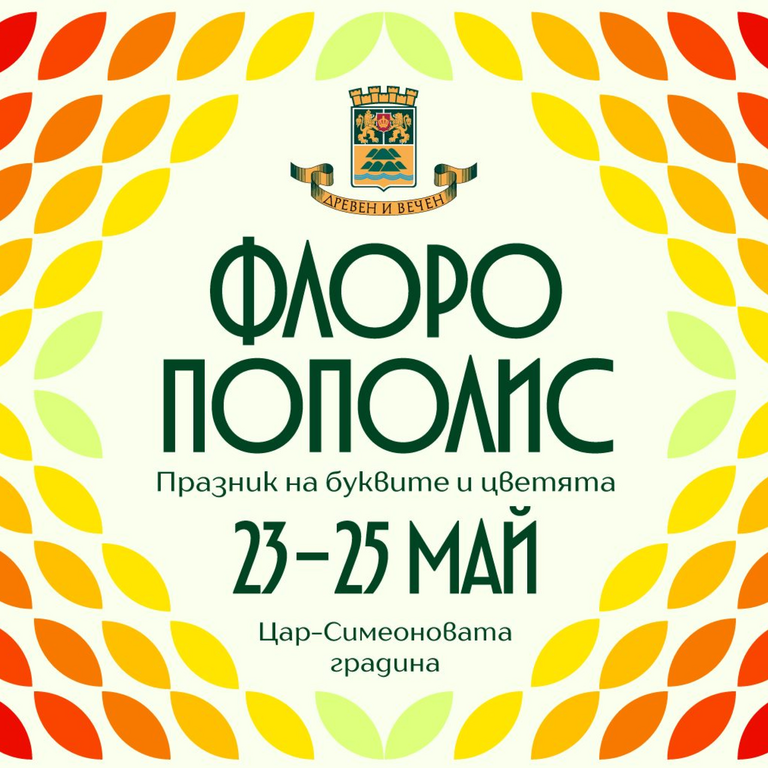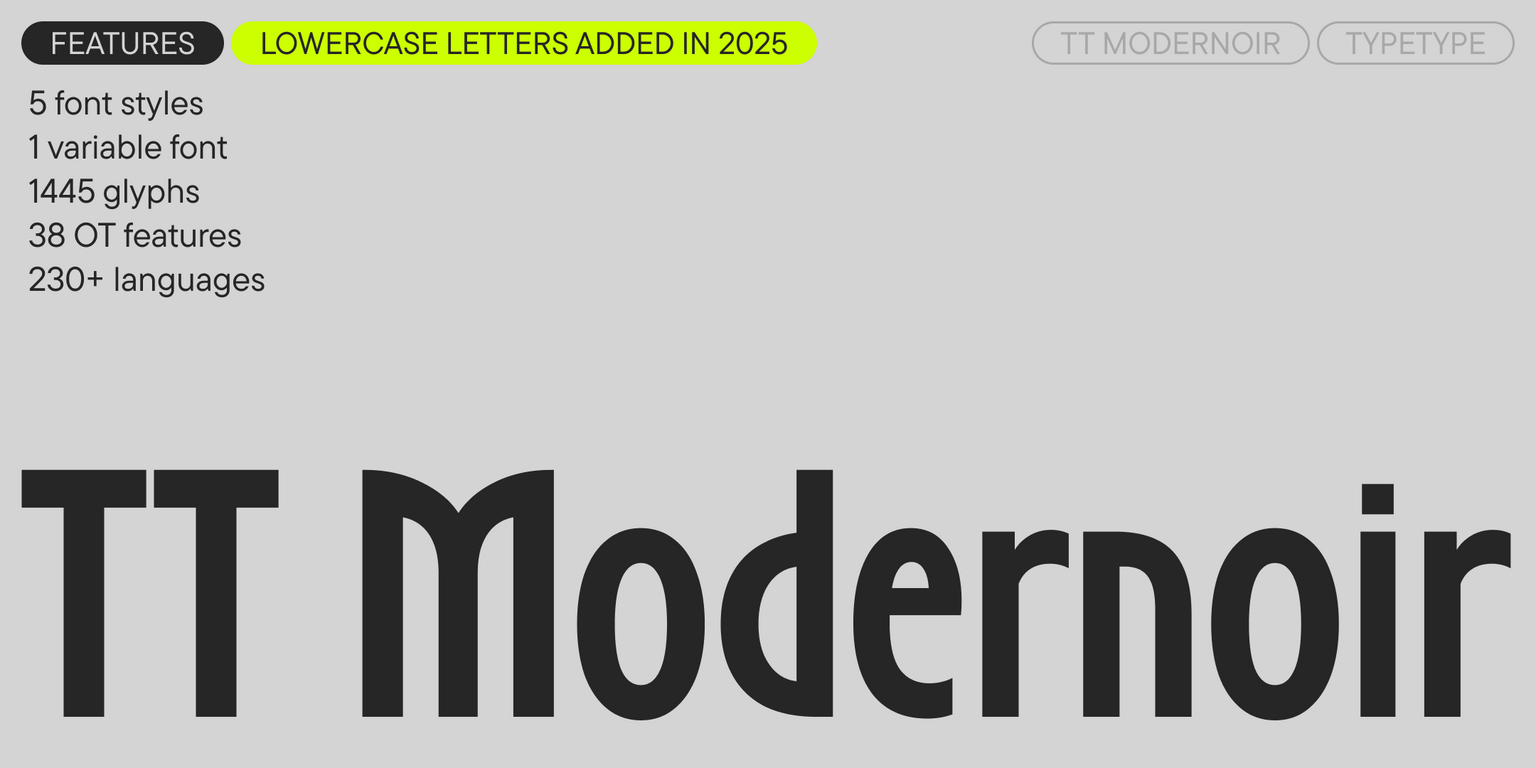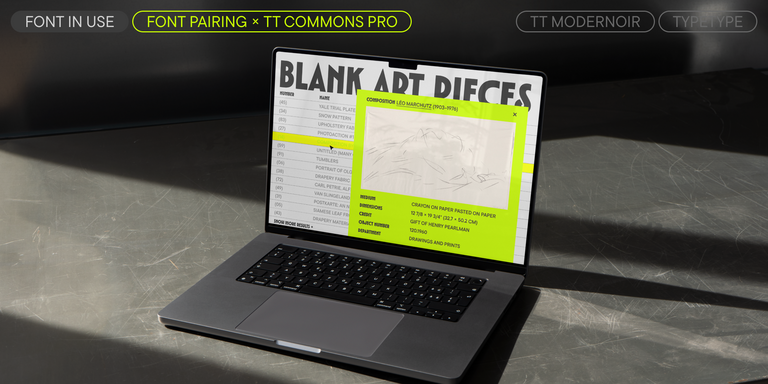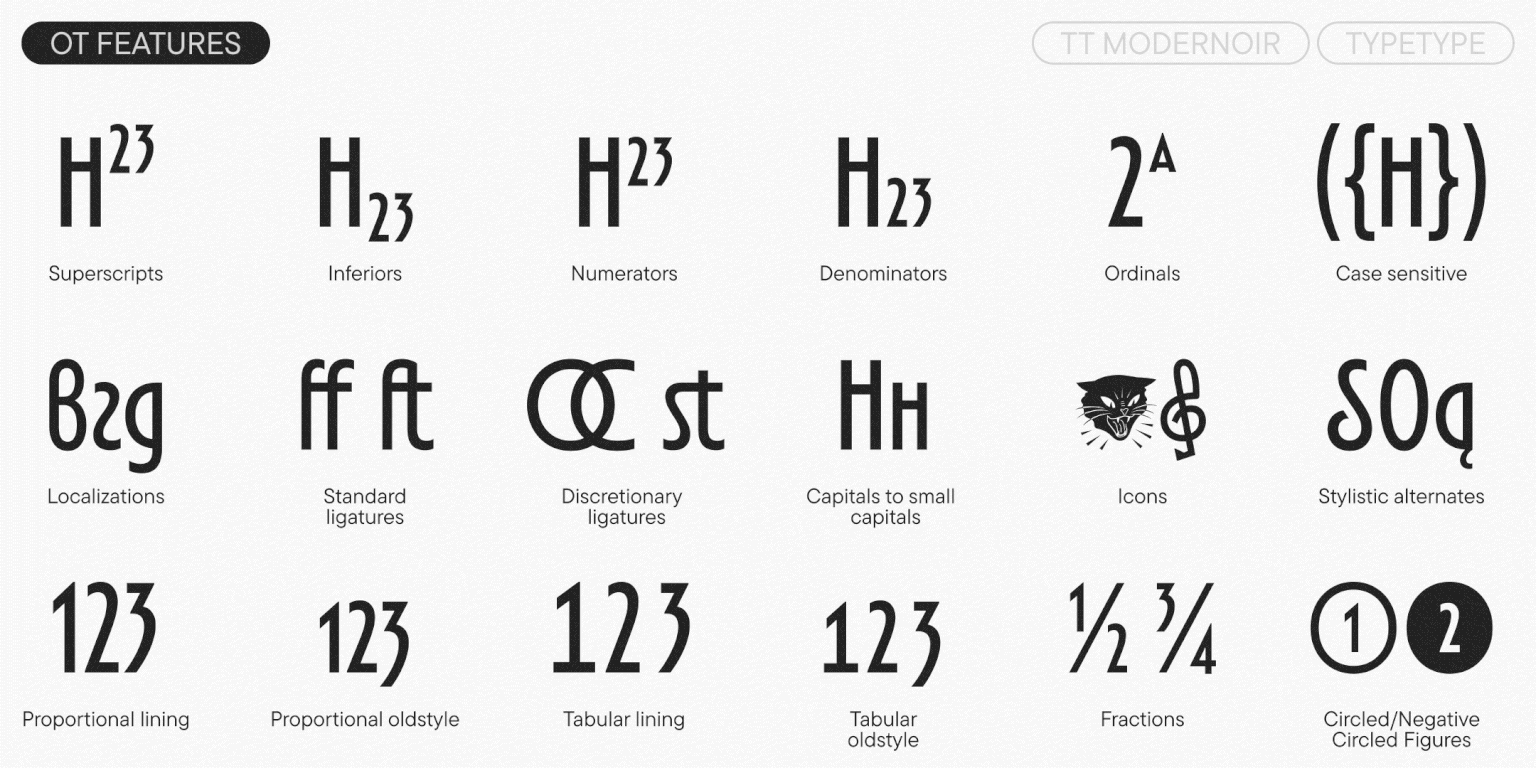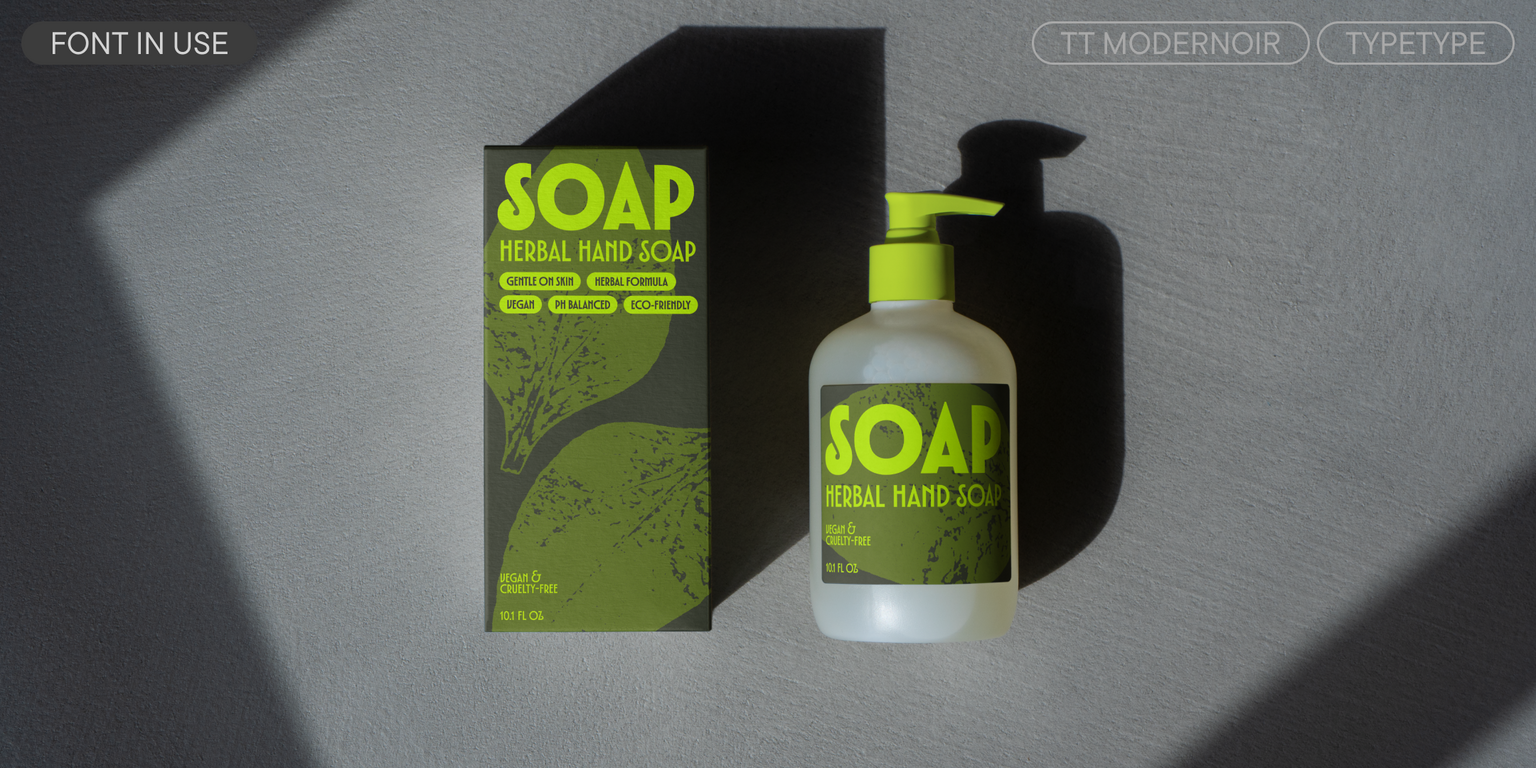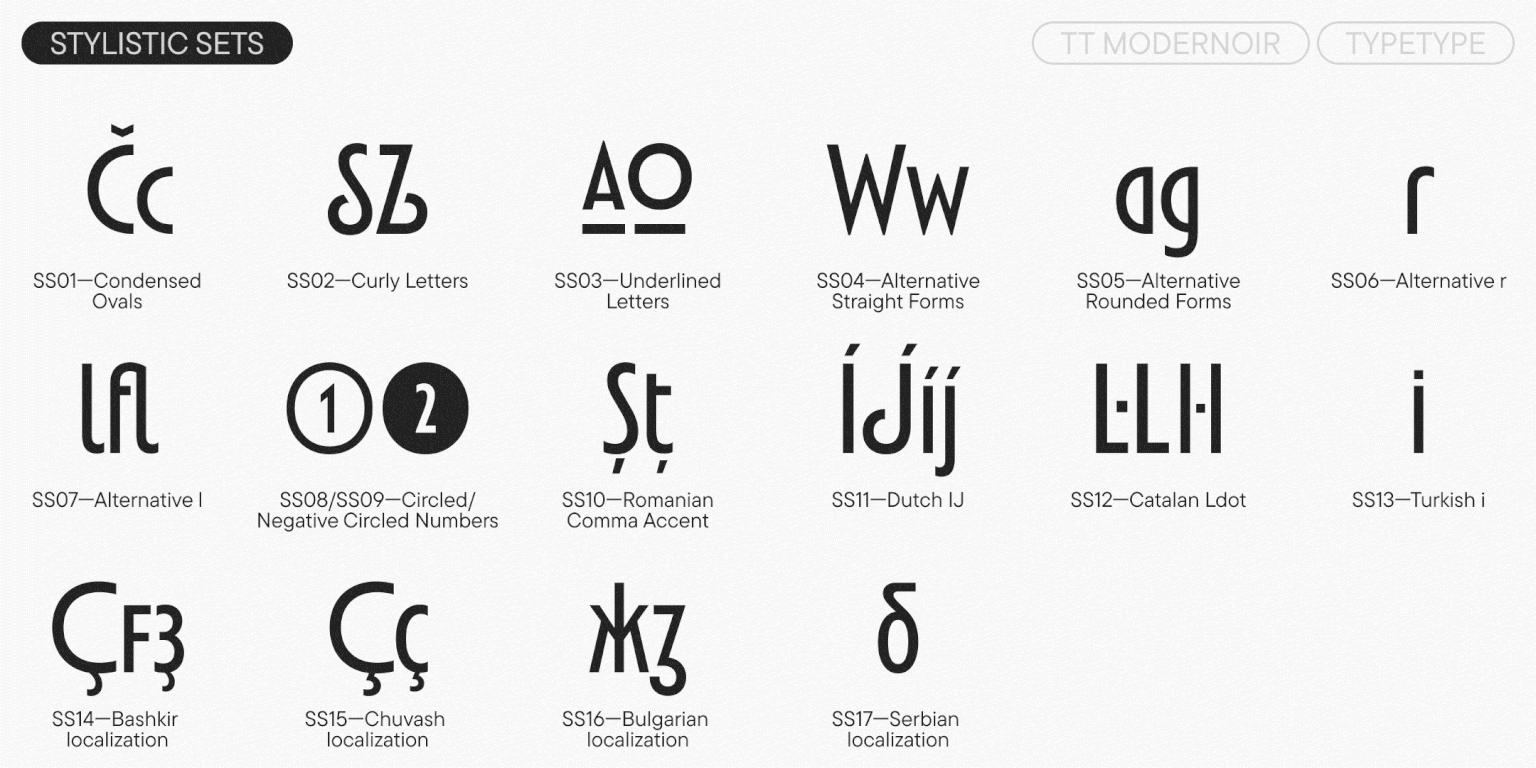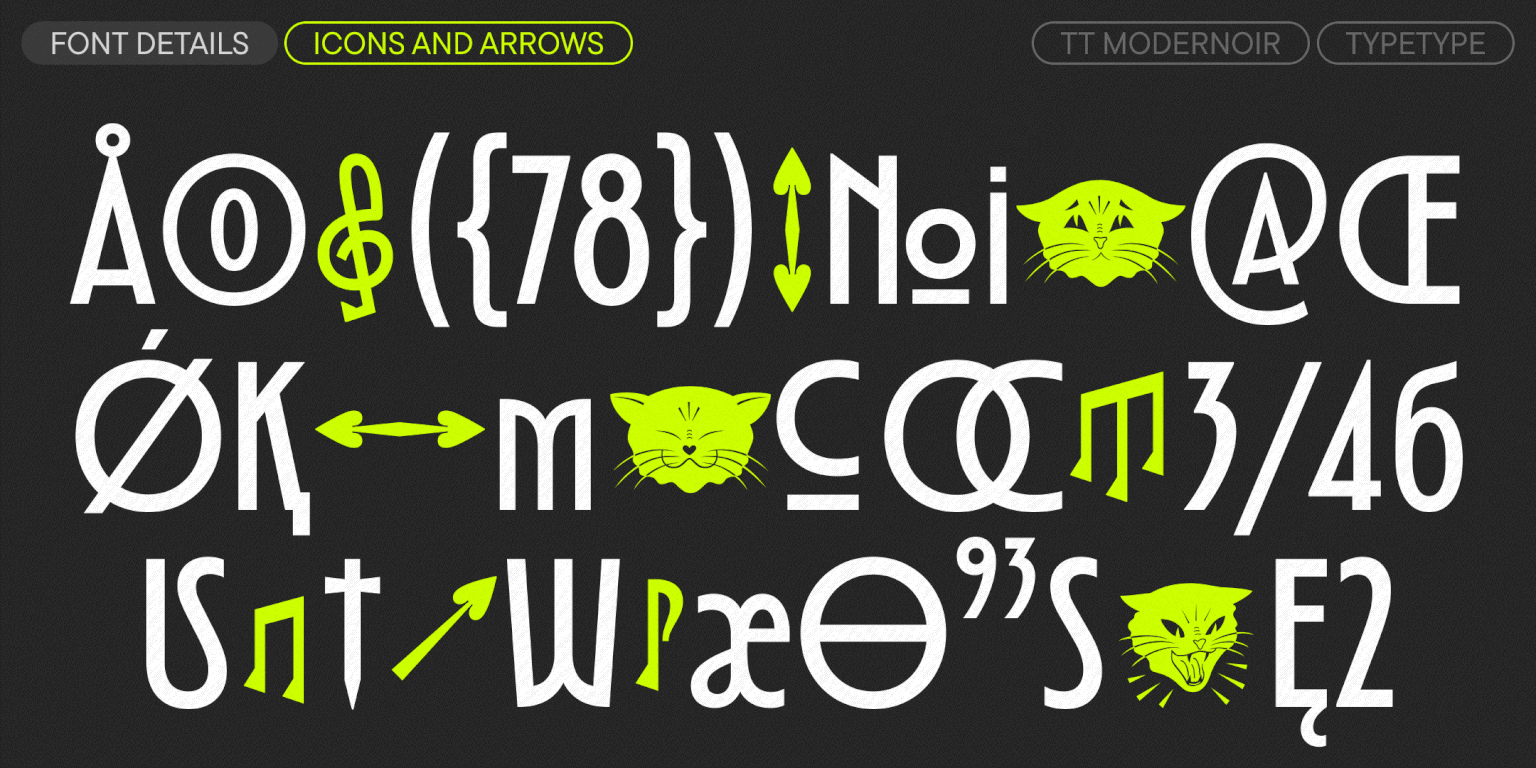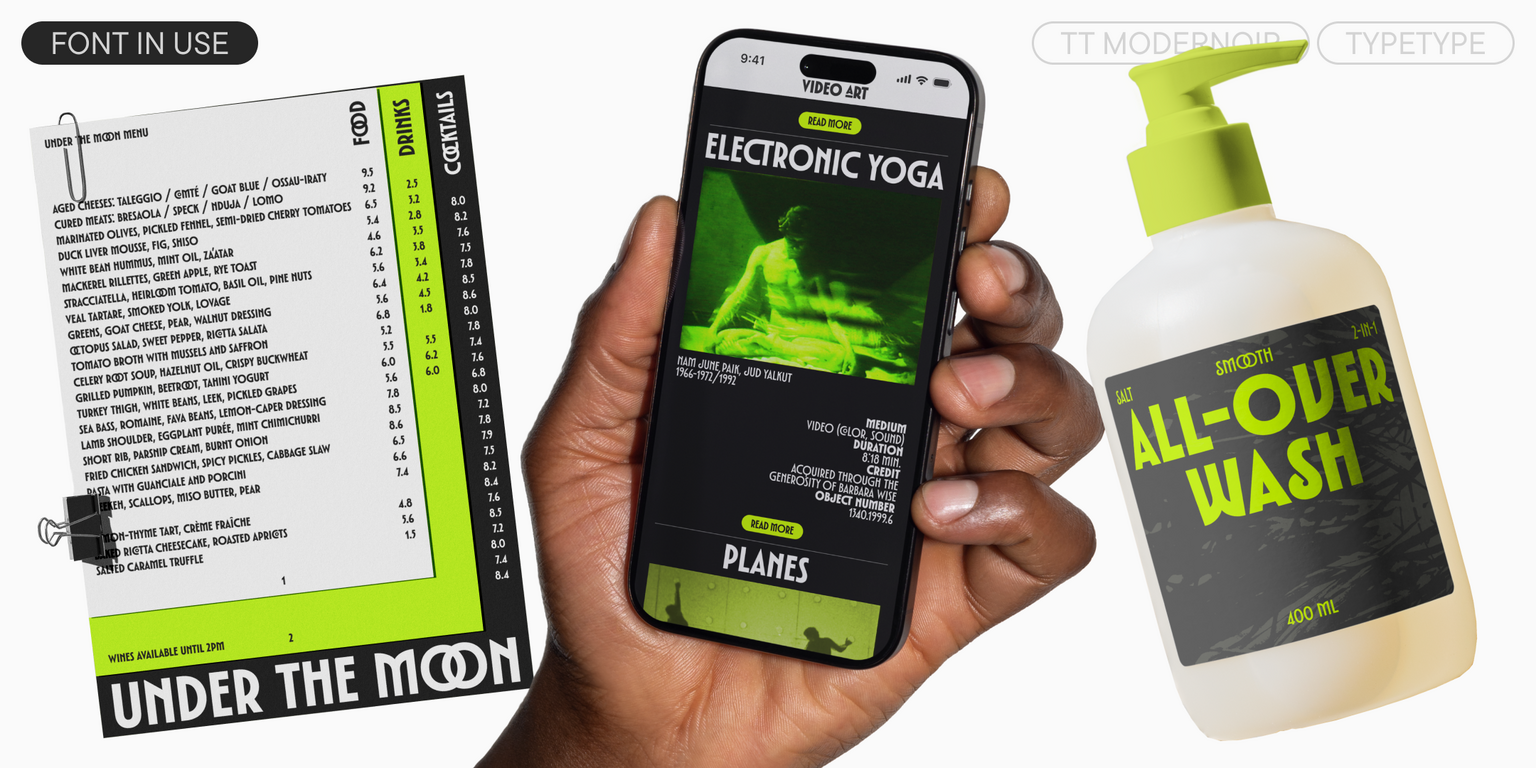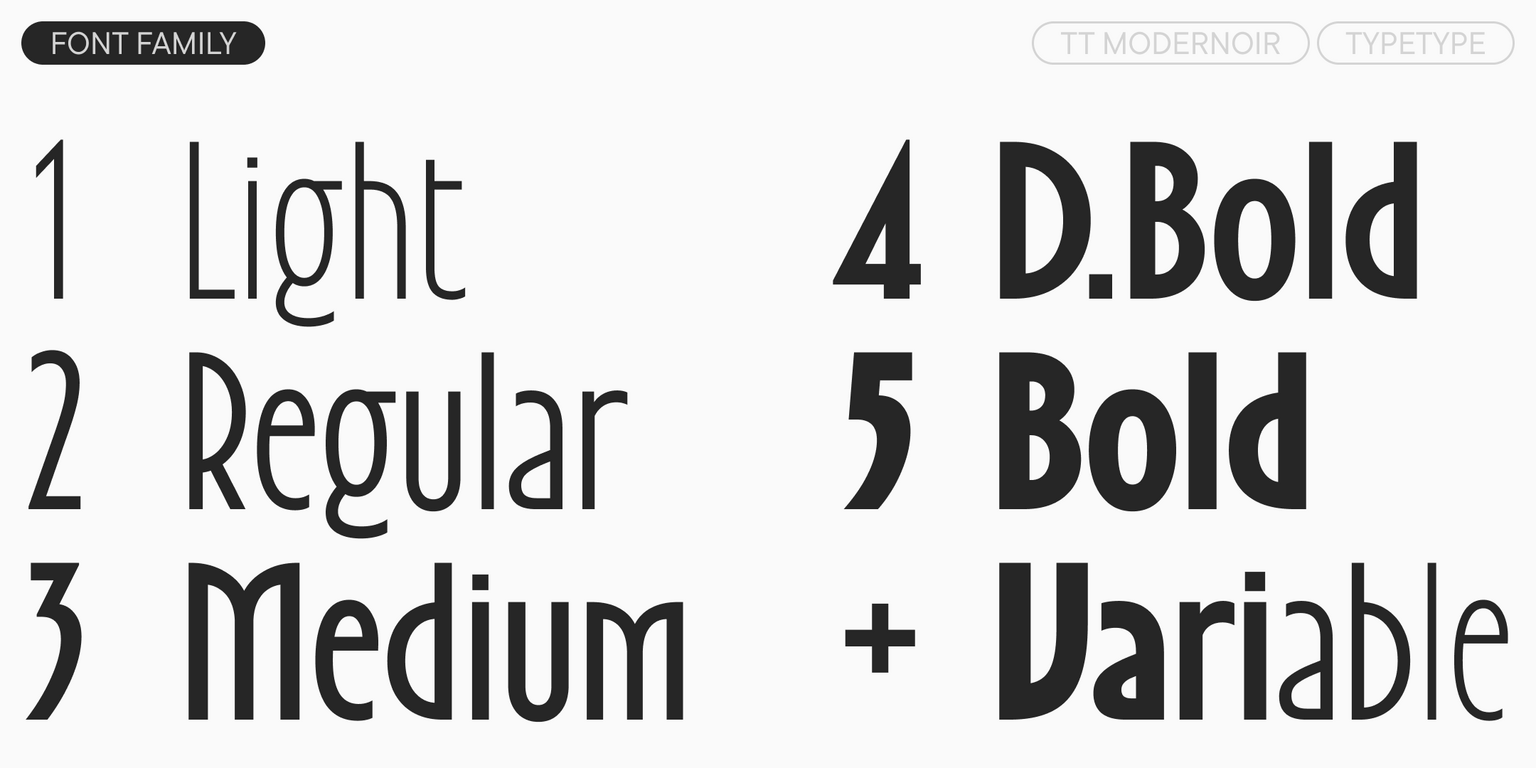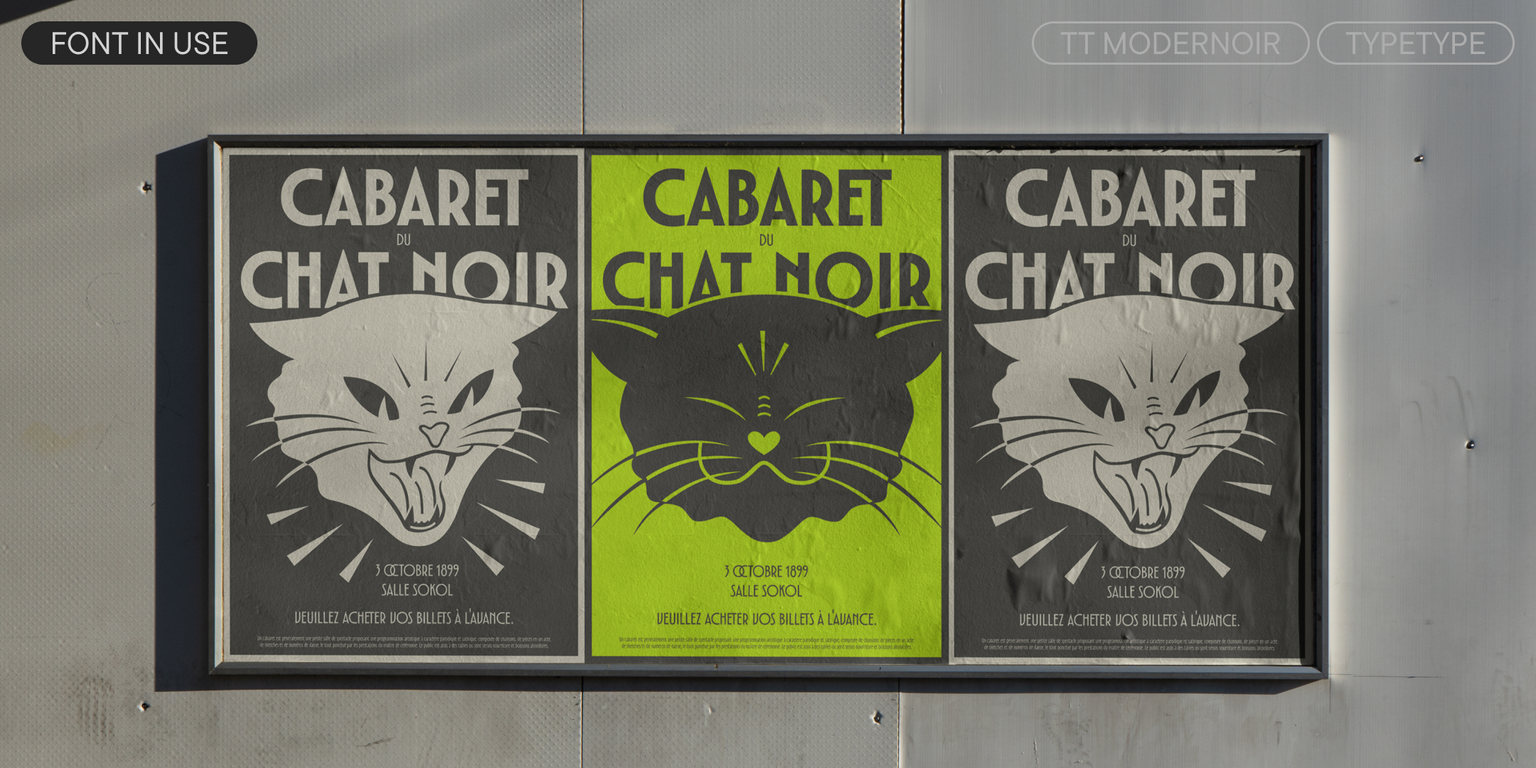
TT Modernoir
TT Modernoir — акцидентный гротеск с разноширинными пропорциями. Плавные линии и изящные формы ар-нуво в нём сочетаются с ритмичностью и свободой джаза.
Встречайте новый суперакцидентный TT Modernoir!
TT Modernoir — акцидентный гротеск с разноширинными пропорциями. Плавные линии и изящные формы ар-нуво в этом шрифте сочетаются с ритмичностью и импровизационной свободой джаза. При его создании мы вдохновлялись французской типографикой XX века, а также эстетикой нуарных фильмов, что отразилось в названии гарнитуры.
Характерные черты TT Modernoir — большая разница в пропорциях прямых и круглых знаков: прямые очень узкие, а круглые, наоборот, очень широкие. Изогнутые ноги букв придают шрифту утонченности, а динамичные завитки создают ощущение музыкального ритма и движения.
Строчных знаков в шрифте нет, но мы предусмотрели капитель для выделения предлогов, небольших слов или других текстовых элементов. Стилистический сет с узкими пропорциями для круглых знаков позволит сделать вид набора более ровным. Сет с подчеркнутыми знаками, напротив, повысит градус акциденции там, где это необходимо. А ещё в гарнитуру входит так называемый «кудрявый сет» с завитками в знаках «S», «Z» и изогнутыми ногами у «R», «Я».
Разнообразить дизайн поможет небольшой сет иконок, среди которых найдутся характерные чёрные коты, стрелы с наконечниками-сердечками и музыкальные ноты. Полезные фичи и вариативный шрифт, меняющийся по оси жирности, дадут возможность подстроить гарнитуру под различные задачи.
Лучше всего TT Modernoir работает в крупном кегле. Он отлично подойдет для афиш мероприятий, вывесок, плакатов, дизайна упаковки, обложек журналов и книг, а также для брендинга и логотипов.
OpenType features
tnum | Tabular Figures
numr | Numerator
dnom | Denominator
sups | Superscript
subs | Subscript
dlig | Discretionary Ligatures
ss01 | Condensed Ovals
ss02 | Curly Letters